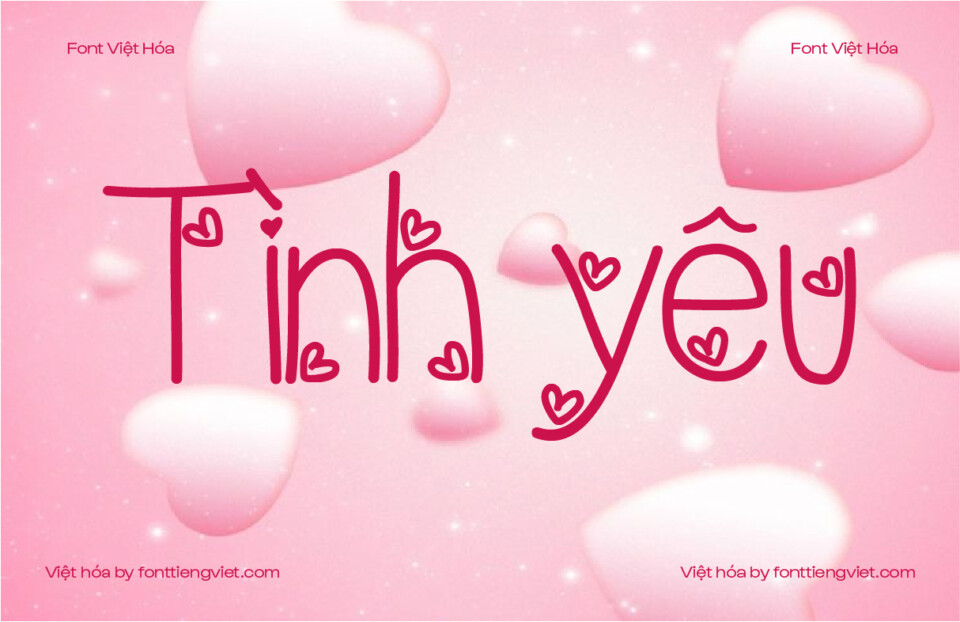
Trong thế giới thiết kế đồ họa đầy sáng tạo, việc lựa chọn một Font Chữ phù hợp có thể tạo nên sự khác biệt lớn, đặc biệt khi bạn muốn truyền tải cảm xúc và phong cách riêng biệt. Hôm nay, chúng ta sẽ cùng khám phá một tuyệt phẩm đang làm mưa làm gió trong cộng đồng thiết kế, đặc biệt là vào mùa yêu thương: Font Việt hóa 1FTV VIP LoveNess Three – Font valentine. Đây không chỉ là một phông chữ thông thường mà còn là biểu tượng của sự lãng mạn, tinh tế và đầy cảm hứng, được tối ưu hóa hoàn hảo cho các dự án cần sự mềm mại, ấm áp và cá nhân hóa.
Với sự phát triển không ngừng của công nghệ và xu hướng thiết kế, nhu cầu về các phông chữ độc đáo, có tính ứng dụng cao và đặc biệt là đã được Việt hóa ngày càng trở nên cấp thiết. Font Việt hóa 1FTV VIP LoveNess Three – Font valentine ra đời để đáp ứng chính xác yêu cầu đó, mang đến một làn gió mới cho các nhà thiết kế đồ họa, học sinh, sinh viên và những ai đam mê sáng tạo nội dung tiếng Việt. Từ thiệp mời, banner quảng cáo cho đến bài đăng mạng xã hội, phông chữ này hứa hẹn sẽ làm bừng sáng mọi ý tưởng của bạn.
Sức hút của Font Việt hóa 1FTV VIP LoveNess Three – Font valentine
Font Việt hóa 1FTV VIP LoveNess Three – Font valentine không chỉ thu hút người dùng bởi cái tên gợi cảm xúc mà còn bởi những đặc tính vượt trội. Điểm nổi bật nhất chính là khả năng Việt hóa hoàn chỉnh, giúp người dùng dễ dàng thể hiện nội dung tiếng Việt một cách mượt mà, không gặp phải lỗi hiển thị ký tự hay dấu. Đây là yếu tố cực kỳ quan trọng đối với thị trường Việt Nam, nơi mà sự chính xác về ngôn ngữ luôn được đề cao trong mọi ấn phẩm truyền thông.
Hơn nữa, phong cách thiết kế của Font Việt hóa 1FTV VIP LoveNess Three – Font valentine mang đậm nét thư pháp hiện đại, với những đường nét uốn lượn mềm mại, bay bổng nhưng vẫn giữ được sự rõ ràng và dễ đọc. Phông chữ này gợi lên cảm giác về tình yêu, sự ngọt ngào và lãng mạn, rất phù hợp cho các dịp đặc biệt như Valentine, kỷ niệm ngày cưới, hay đơn giản là những thông điệp yêu thương hàng ngày. Sự sang trọng nhưng không kém phần gần gũi chính là điểm cộng lớn, giúp phông chữ này trở thành lựa chọn hàng đầu cho nhiều dự án.
Ứng dụng đa dạng của Font Việt hóa 1FTV VIP LoveNess Three – Font valentine
Tính linh hoạt là một trong những ưu điểm khiến Font Việt hóa 1FTV VIP LoveNess Three – Font valentine được đánh giá cao. Phông chữ này có thể được ứng dụng trong vô số lĩnh vực khác nhau, từ cá nhân đến chuyên nghiệp, mang lại hiệu quả thẩm mỹ cao và góp phần truyền tải thông điệp một cách hiệu quả nhất.
Thiết kế thiệp và quà tặng: Với chủ đề valentine, phông chữ này là lựa chọn hoàn hảo để tạo ra những tấm thiệp chúc mừng, hộp quà tặng hay các ấn phẩm in ấn mang đậm dấu ấn cá nhân và tình cảm. Các nét chữ bay bổng sẽ làm cho thông điệp yêu thương thêm phần lãng mạn và ý nghĩa.
Truyền thông mạng xã hội: Trong thời đại số, việc tạo ra nội dung thu hút trên Facebook, Instagram hay TikTok là vô cùng quan trọng. Font Việt hóa 1FTV VIP LoveNess Three – Font valentine giúp các bài đăng, story hay banner quảng cáo của bạn trở nên nổi bật, chuyên nghiệp và đầy cảm xúc, thu hút sự chú ý của người xem.
Thiết kế thương hiệu: Đối với các thương hiệu về thời trang, mỹ phẩm, ẩm thực cao cấp hay các dịch vụ cưới hỏi, việc sử dụng phông chữ này có thể giúp xây dựng một hình ảnh sang trọng, tinh tế và đáng nhớ. Nó tạo ra một phong cách độc đáo, khó lẫn vào đâu được.
In ấn và xuất bản: Từ sách truyện, tạp chí cho đến các ấn phẩm nghệ thuật, Font Việt hóa 1FTV VIP LoveNess Three – Font valentine mang lại vẻ đẹp cổ điển kết hợp hiện đại, làm cho văn bản trở nên hấp dẫn và dễ đọc hơn, đặc biệt khi nó được sử dụng cho các tiêu đề hoặc phần nhấn nhá.
Phông chữ này cũng rất phù hợp cho các dự án cá nhân của học sinh, sinh viên khi làm bài tập trình bày, poster, hoặc các dự án sáng tạo tại trường. Sự dễ dùng và vẻ đẹp của nó sẽ giúp các bạn tự tin hơn trong việc thể hiện ý tưởng.
Lợi ích khi lựa chọn Font Việt hóa 1FTV VIP LoveNess Three – Font valentine
Việc đầu tư vào một phông chữ chất lượng như Font Việt hóa 1FTV VIP LoveNess Three – Font valentine mang lại nhiều lợi ích đáng kể, đặc biệt là trong bối cảnh cạnh tranh khốc liệt của ngành thiết kế và truyền thông hiện nay.
Đầu tiên, đây là một “font VIP” đúng nghĩa, mang đến một đẳng cấp khác biệt so với các phông chữ miễn phí thông thường. Chất lượng thiết kế cao, sự chăm chút tỉ mỉ trong từng đường nét và khả năng tương thích tốt với các phần mềm thiết kế chuyên nghiệp là những gì bạn có thể mong đợi. Điều này giúp các sản phẩm của bạn trông chuyên nghiệp và độc đáo hơn, tạo ấn tượng mạnh mẽ với người xem.
Thứ hai, khả năng Việt hóa hoàn chỉnh giúp loại bỏ mọi lo ngại về vấn đề hiển thị font chữ tiếng Việt. Bạn không cần phải tốn thời gian căn chỉnh hay sửa lỗi, chỉ cần tập trung vào nội dung và ý tưởng sáng tạo. Đây là một lợi thế lớn, đặc biệt khi làm việc với các dự án có thời hạn gấp.
Cuối cùng, việc sở hữu và sử dụng Font Việt hóa 1FTV VIP LoveNess Three – Font valentine cũng thể hiện sự nghiêm túc và chuyên nghiệp của bạn trong công việc. Một phông chữ đẹp, độc đáo và được sử dụng đúng cách sẽ nâng tầm giá trị cho tác phẩm của bạn, giúp bạn nổi bật hơn trong mắt khách hàng hoặc đối tác.
Tóm lại, Font Việt hóa 1FTV VIP LoveNess Three – Font valentine không chỉ là một phông chữ đơn thuần mà còn là nguồn cảm hứng bất tận cho những ai muốn thể hiện tình yêu và sự lãng mạn qua từng nét chữ. Từ thiệp cưới, poster quảng cáo đến các dự án cá nhân, phông chữ này mang đến vẻ đẹp tinh tế, sang trọng và đầy cảm xúc. Hãy để Font Chữ đặc biệt này nâng tầm các dự án thiết kế của bạn, giúp bạn tạo ra những tác phẩm nghệ thuật độc đáo và ghi dấu ấn sâu đậm trong lòng người xem. Với sự kết hợp hoàn hảo giữa thẩm mỹ và tính năng, nó chắc chắn sẽ trở thành một công cụ không thể thiếu trong bộ sưu tập font chữ của bạn.